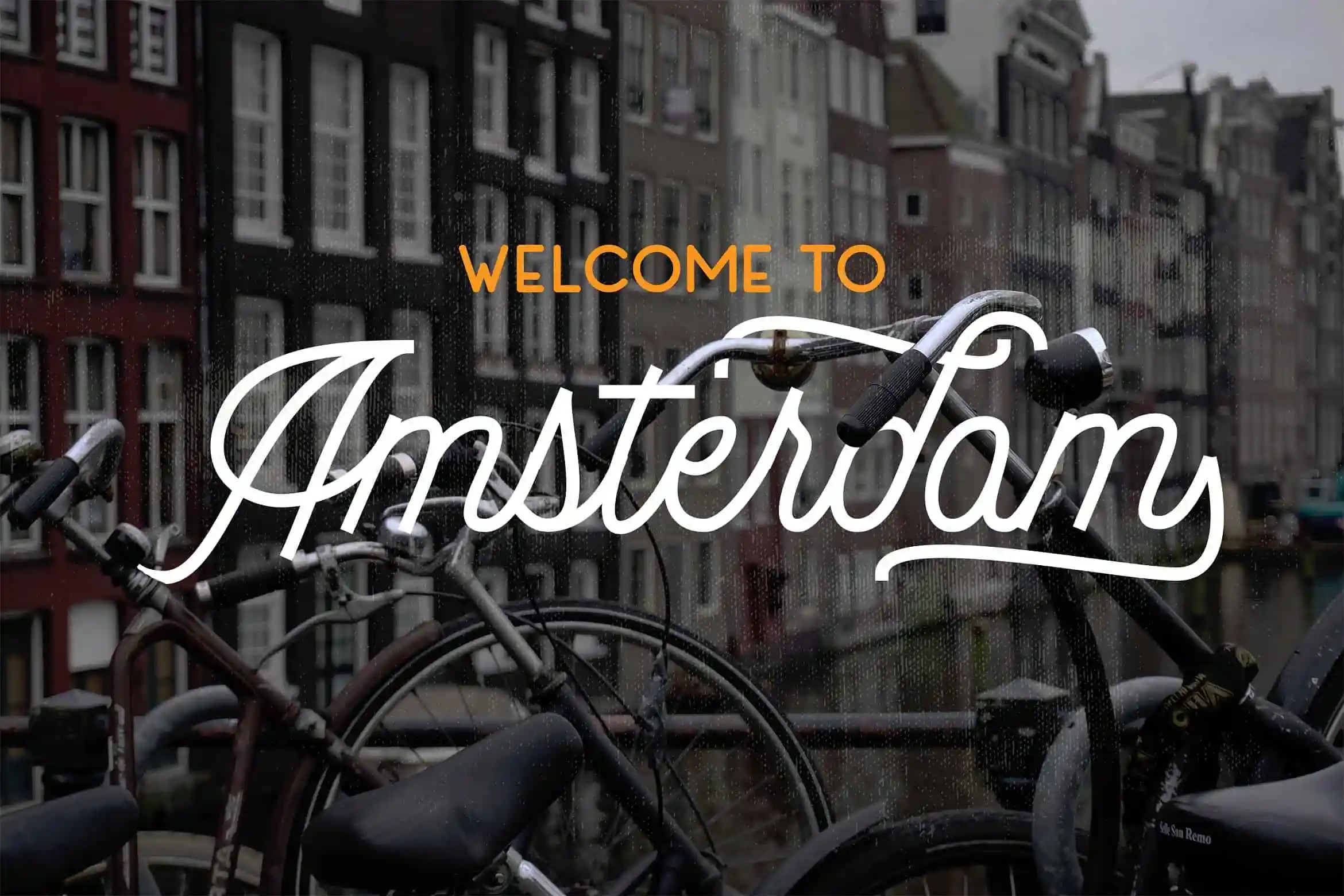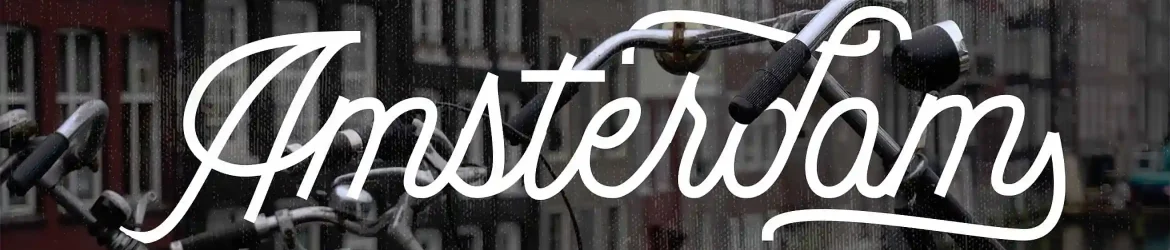
Aqui está uma descrição envolvente e natural para a página de download da fonte ‘Dingbod Script and Sans Font’, focada no seu design inspirado em postais clássicos: Introduzimos Dingbod, uma autêntica mistura de script e sans-serif que ganha vida através do toque artesanal. Inspirada nos desafios visuais dos posters antigos, essa fonte foi projetada para despertar emoções e transmitir personalidade. Seja você um designer gráfico ou estilista de moda, pode explorar a versatilidade desta fonte em suas criações. Dingbod Script e Sans contém todos os elementos essenciais: letras maiúsculas e minúsculas, números e um leque amplo de pontuação. E, o que torna essa fonte ainda mais especial, são as alternativas do tipo aberto, ligações comuns e swashes adicionais para que você possa personalizar suas criações a seu modo. Adaptável para nomes de marca, cartões de visita, propaganda, design de roupas ou etiquetas, Dingbod atende todas essas necessidades e mais. Seja qual seja o projeto em que estiver aplicando essa fonte, ela certamente dará um toque único à sua obra.